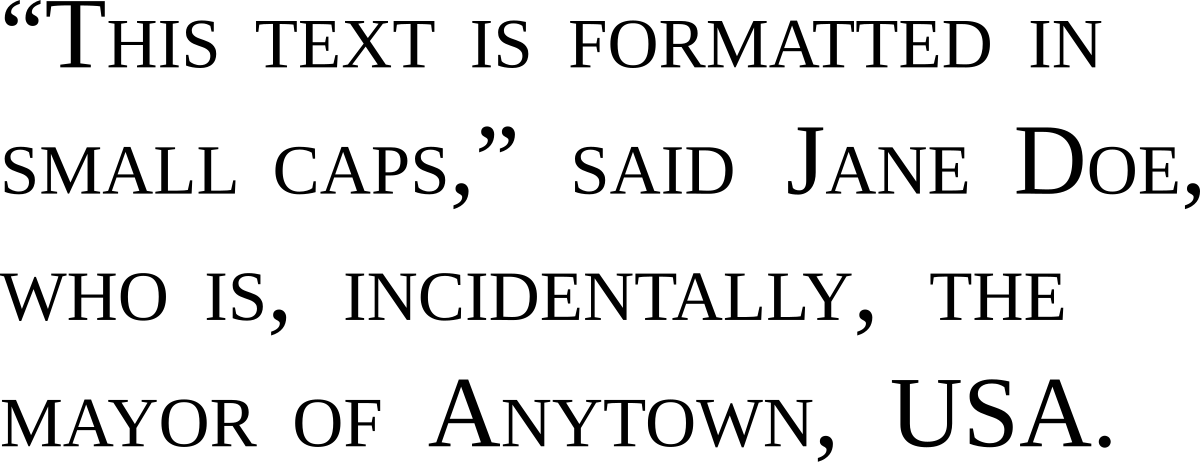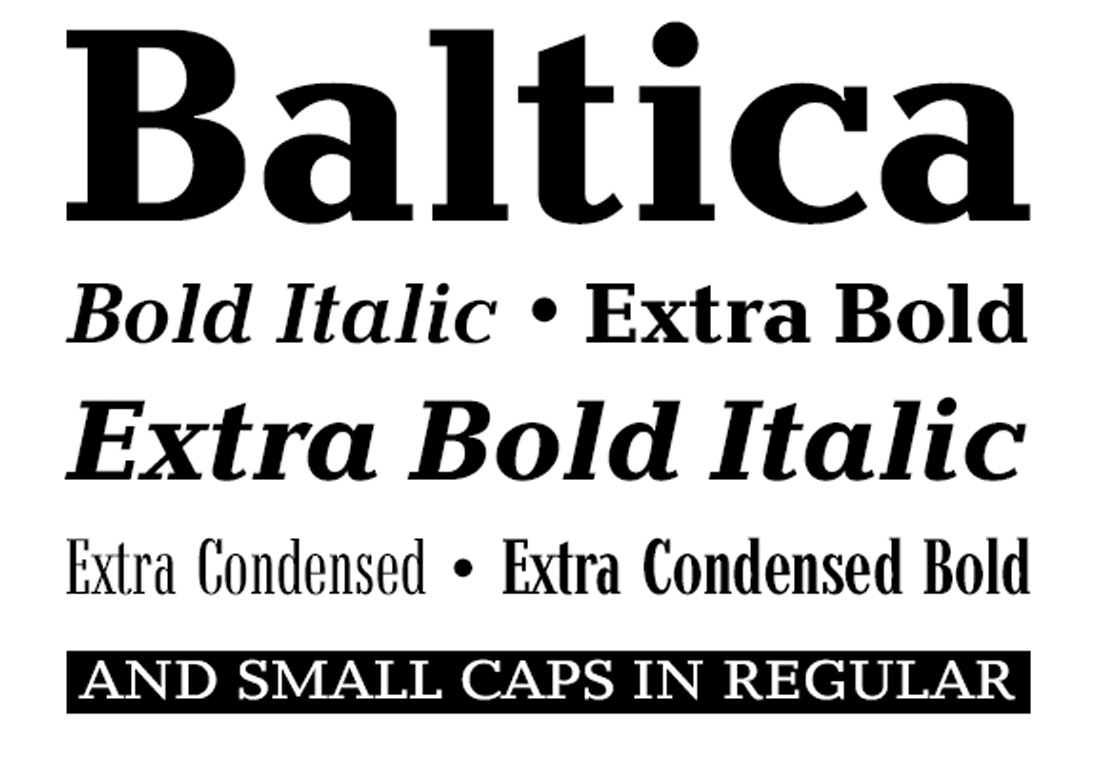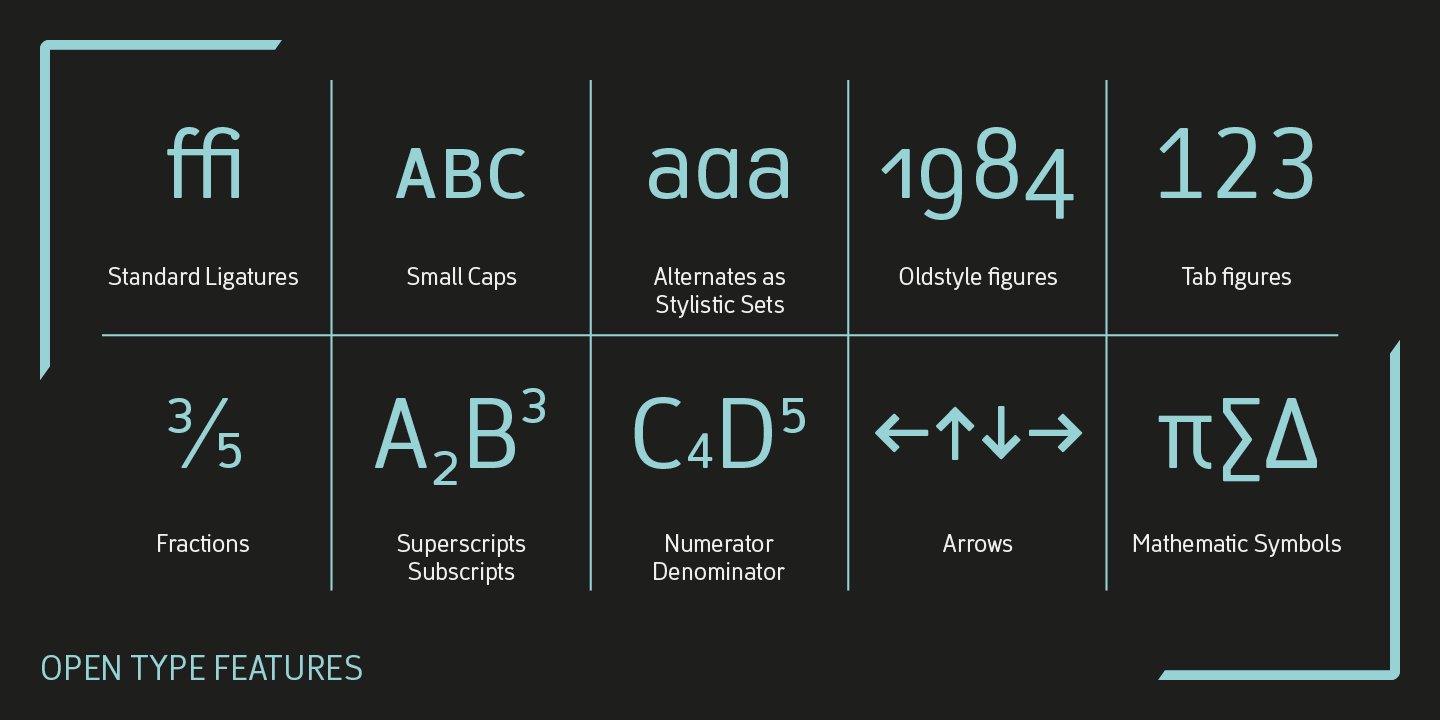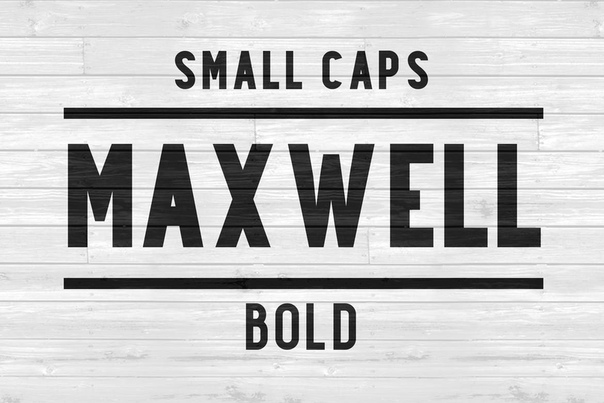
Капитель (шрифт)
орматирование символовА А a А a
Несколько раз написана одна и та же буква. Но нетрудно заметить, что эти буквы отличаются друг от друга начертанием и размером. Можно делать их разного цвета. Так как вся работа в тестовом редакторе связана со шрифтами, то о них и поговорим.
Шрифт — это набор графического представления цифр, букв и символов. Шрифт имеет определенную гарнитуру, а также другие свойства, такие как размер, интервал и наклон.
Гарнитура шрифта — это набор начертаний одного шрифта. Шрифт может иметь «прямое» начертание(noramal), курсив(italic), усиленное по насыщенности («жирное», bold), «мелкое»(капитель, small-caps) и т.п.. Наиболее распространненые гарнитуры — это Times, Arial, Courier. Причем все они принадлежат к разным группам шрифтов. Times — это пропорциональный шрифт «с засечками»(serif), Arial — это пропорциональный шрифт «без засечек»(sans-serif), а Courier — это моноширинный шрифт (monospace). В чем разница между этими группами шрифтов лучше всего видно на примере:
Эта строка набрана пропорциональным шрифтом с засечками.
Эта строка набрана пропорциональным шрифтом без засечек.